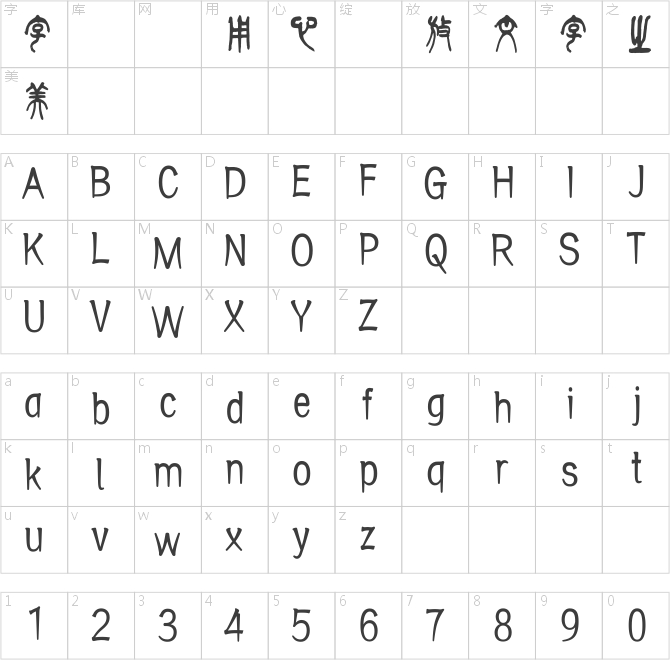
方正字跡-曾彩初篆書 詳情頁
方正字跡-曾彩初篆書字體下載
方正字跡-曾彩初篆書,由著名書畫家、教育家曾彩初先生創(chuàng)作。曾彩初先生為中國書法家協(xié)會(huì)會(huì)員、湖南省書法家協(xié)會(huì)會(huì)員。這款字體取法《說文解字》,融合大篆與小篆而自成一體,以圓筆藏鋒為主書寫而成,字形修長、上密下疏呈現(xiàn)出甲骨文、金文的古樸厚重、渾厚宏偉之氣,又具小篆端莊典雅的美感,既植根傳統(tǒng)又彰顯個(gè)性。適用于有傳統(tǒng)文化底蘊(yùn)的藝術(shù)觀賞和宣傳、刻石、刻印、廣告包裝、書籍裝幀設(shè)計(jì)、書畫標(biāo)題。